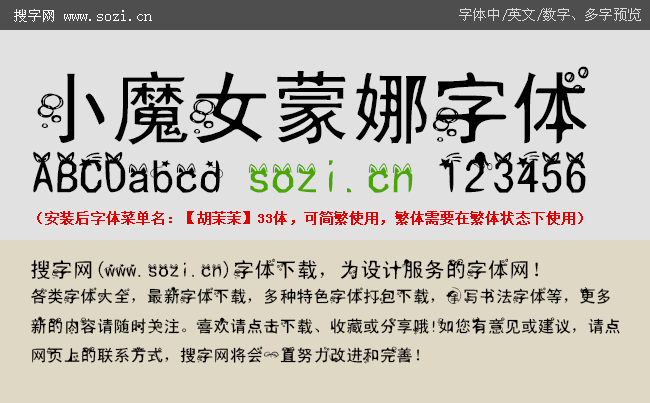
小魔女蒙娜字體
搜字網(wǎng)給大家提供一款小魔女蒙娜字體手機(jī)中文字體下載。這款手機(jī)字體是將黑體字體的筆畫中裝飾上了可愛的卡通圖案。即有黑體字端正易認(rèn)的特點,又帶有一點卡通風(fēng)格,是一款非?蓯鄣目ㄍㄗ煮w,特別適合喜歡手機(jī)字體個性一些的朋友在手機(jī)上安裝使用。